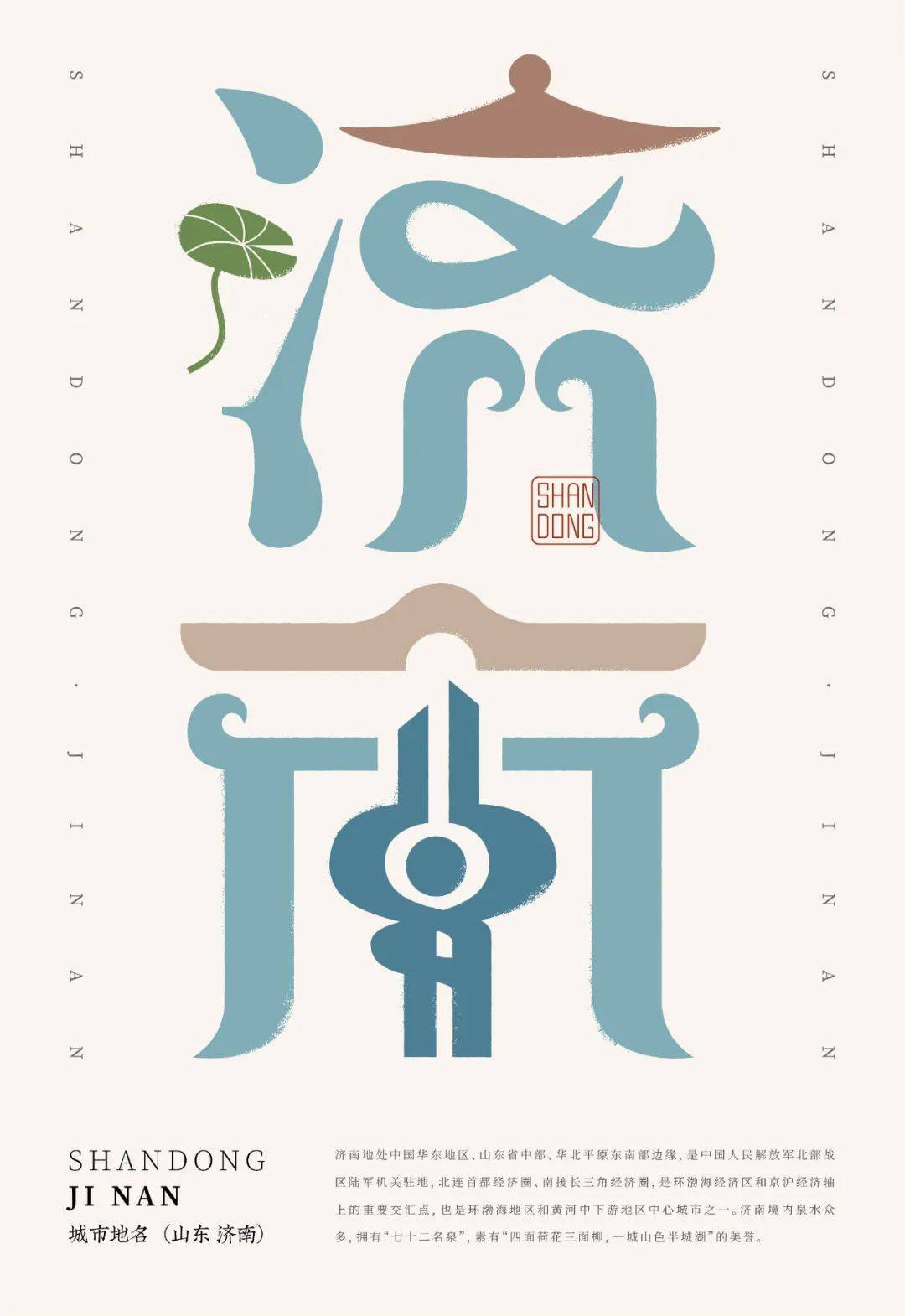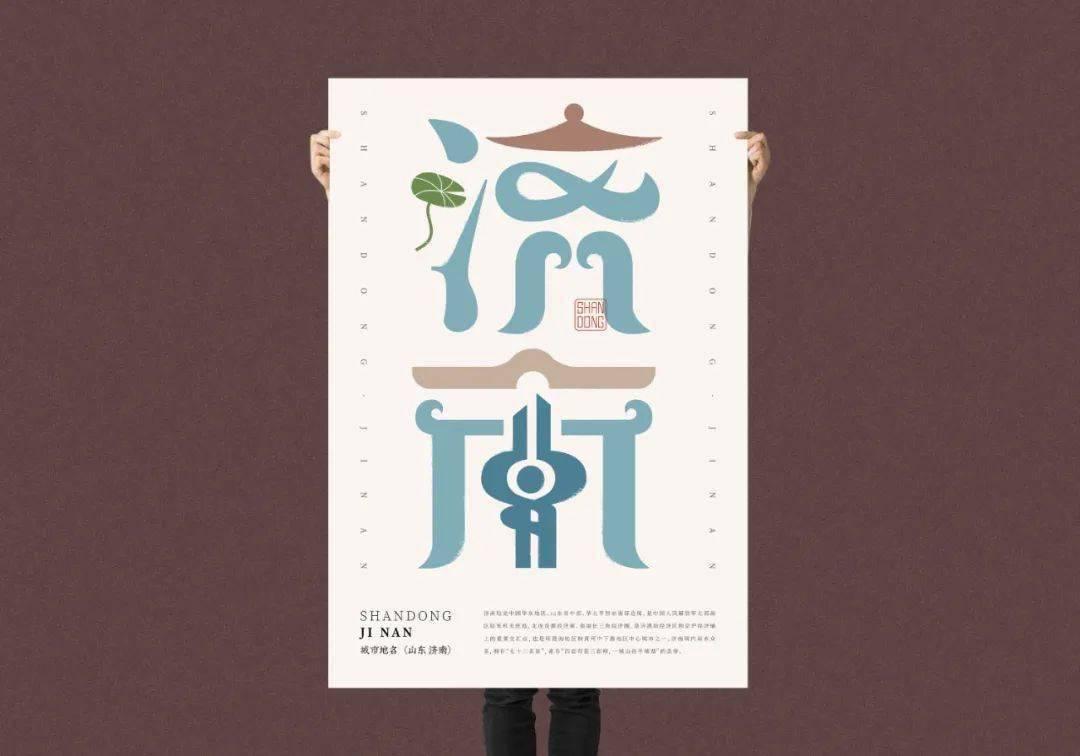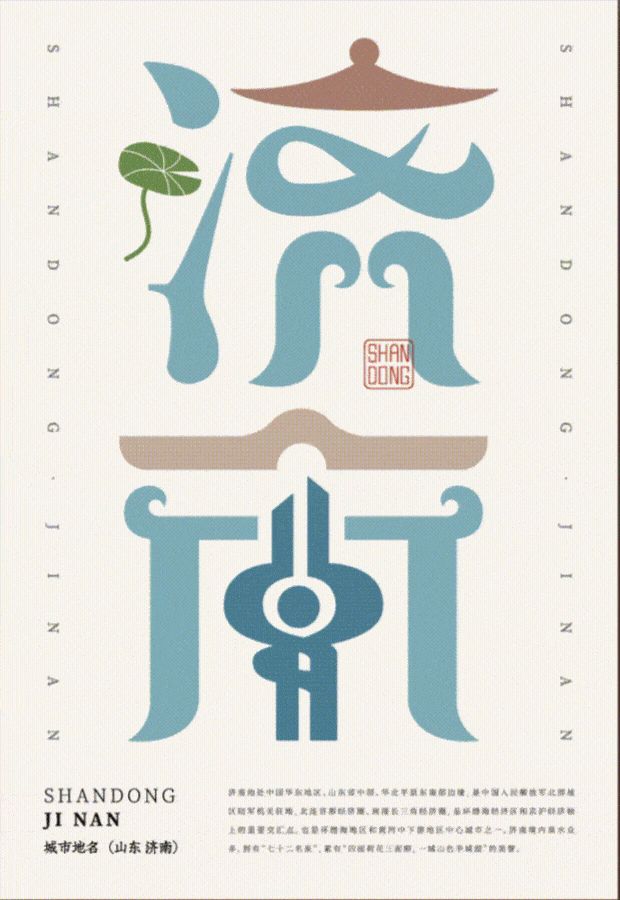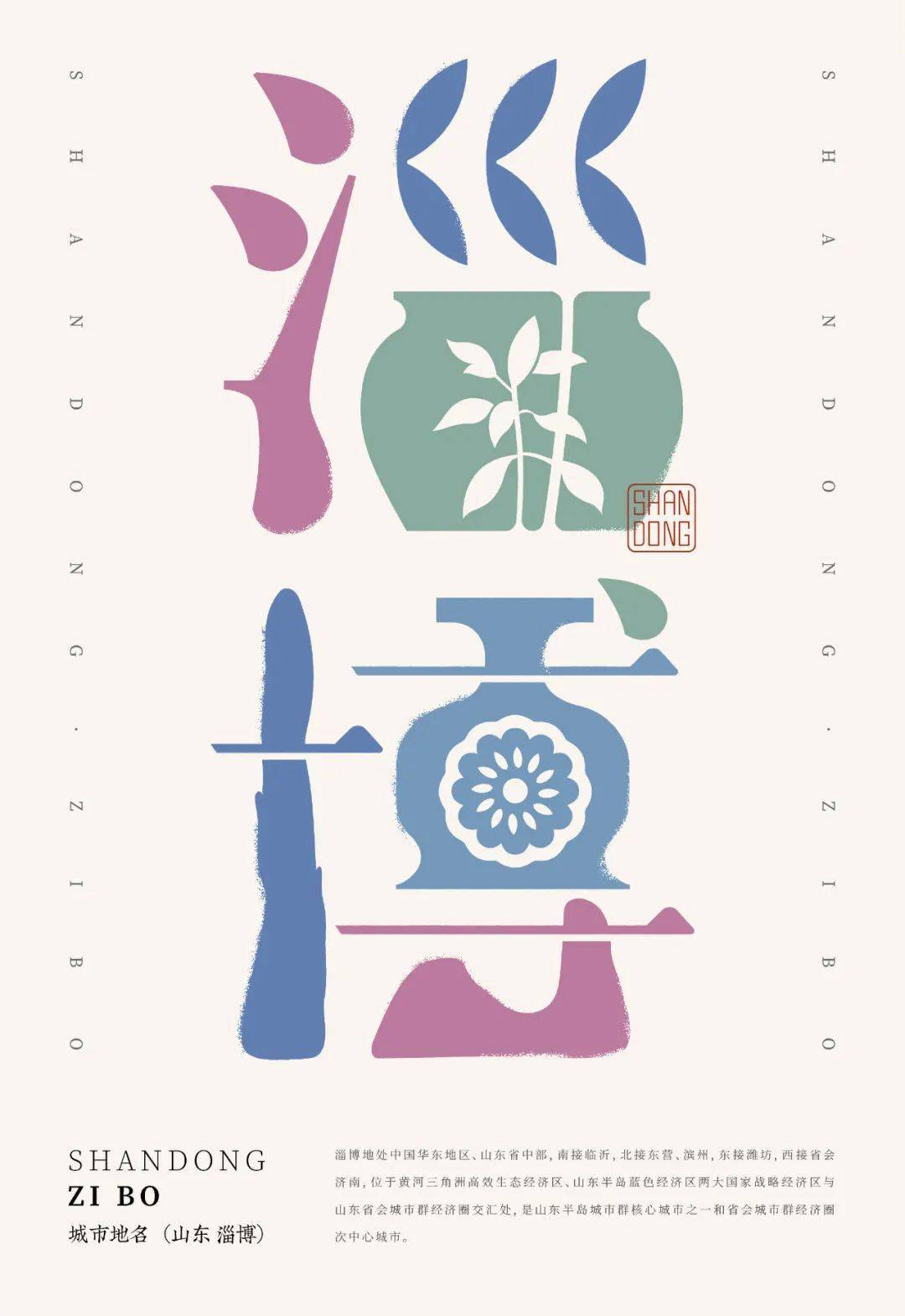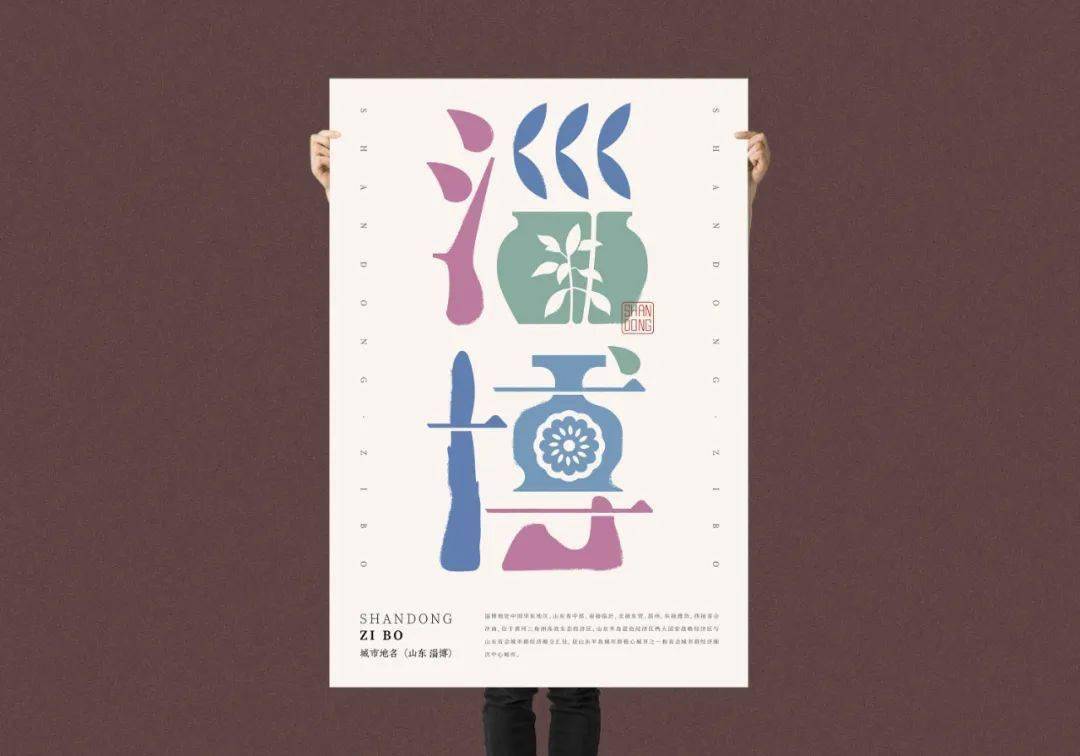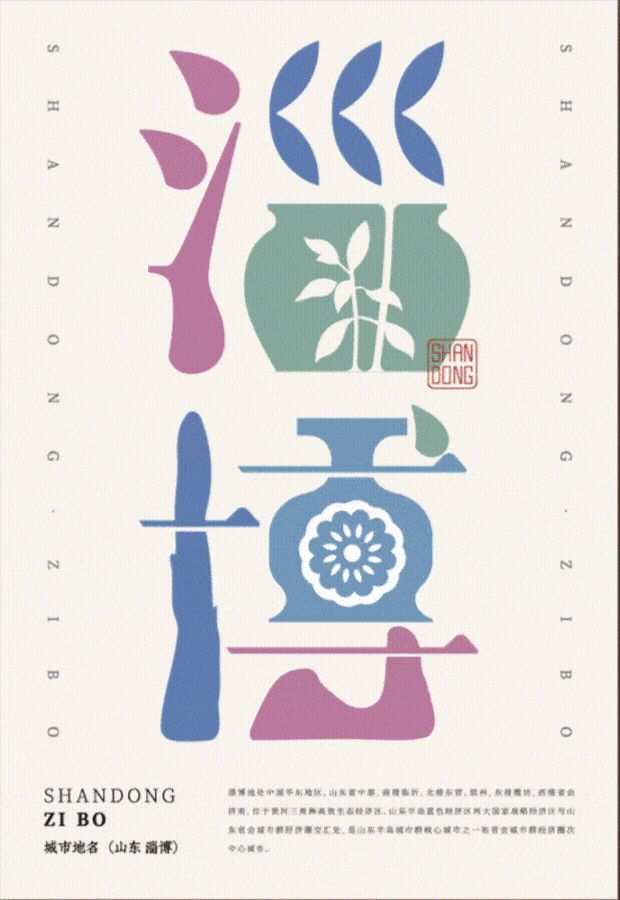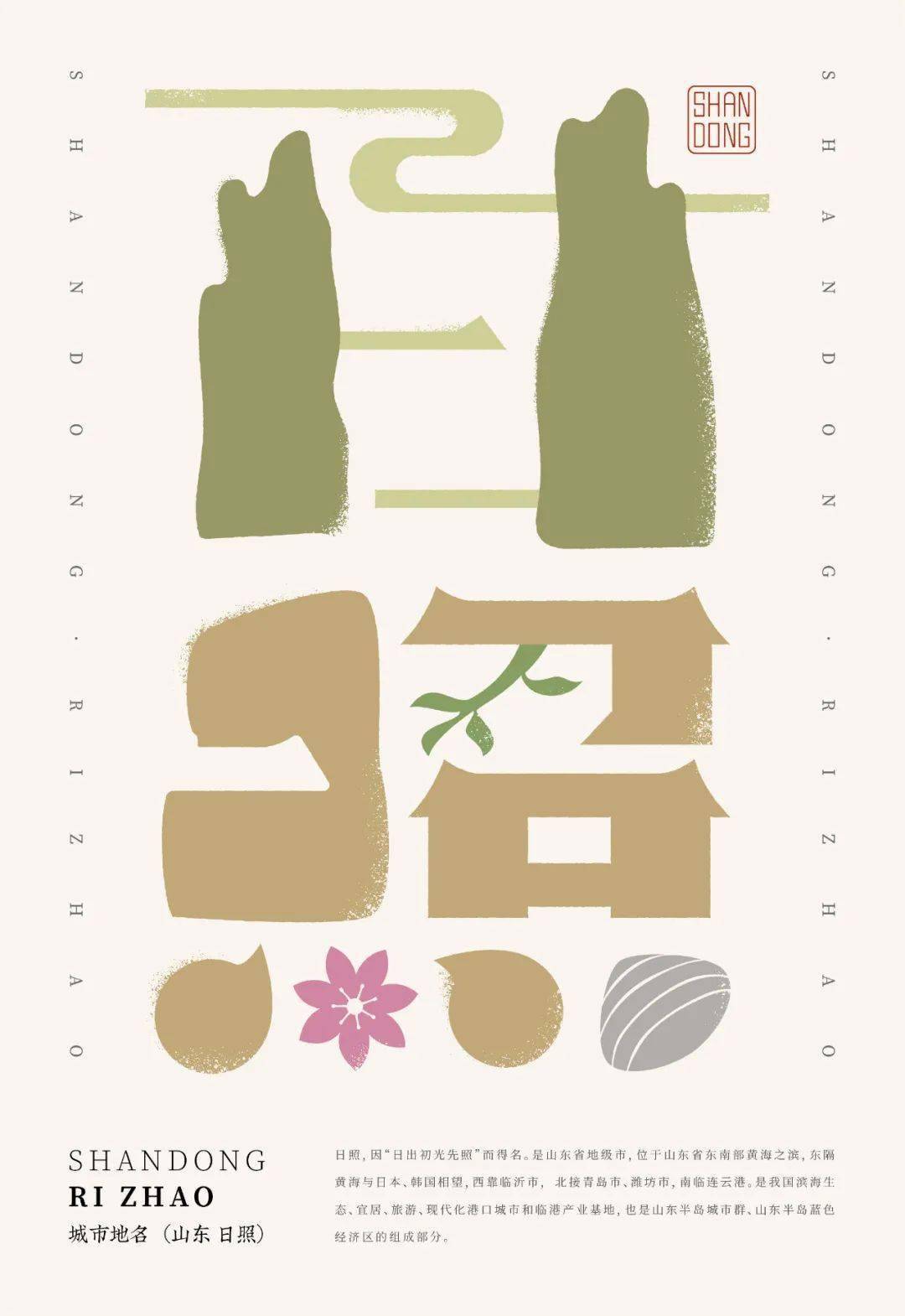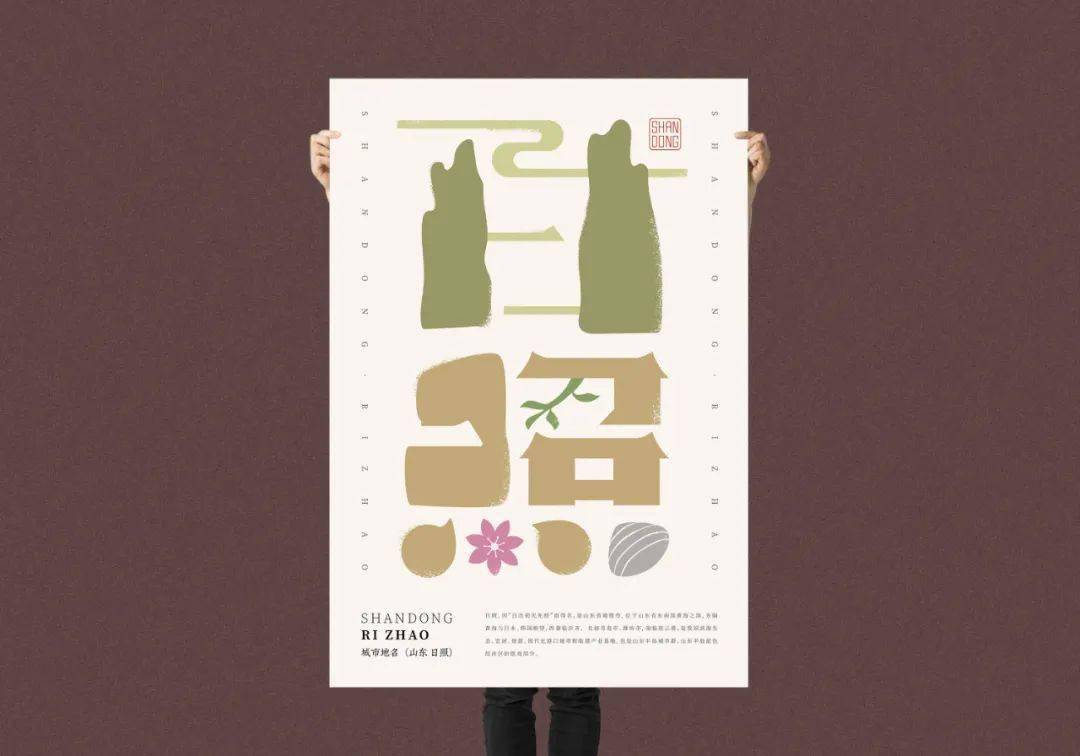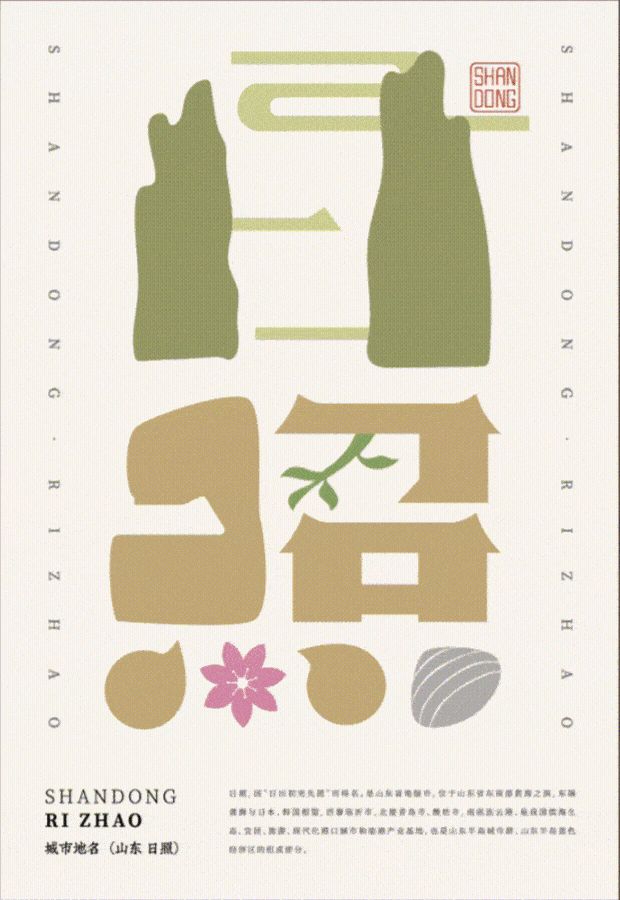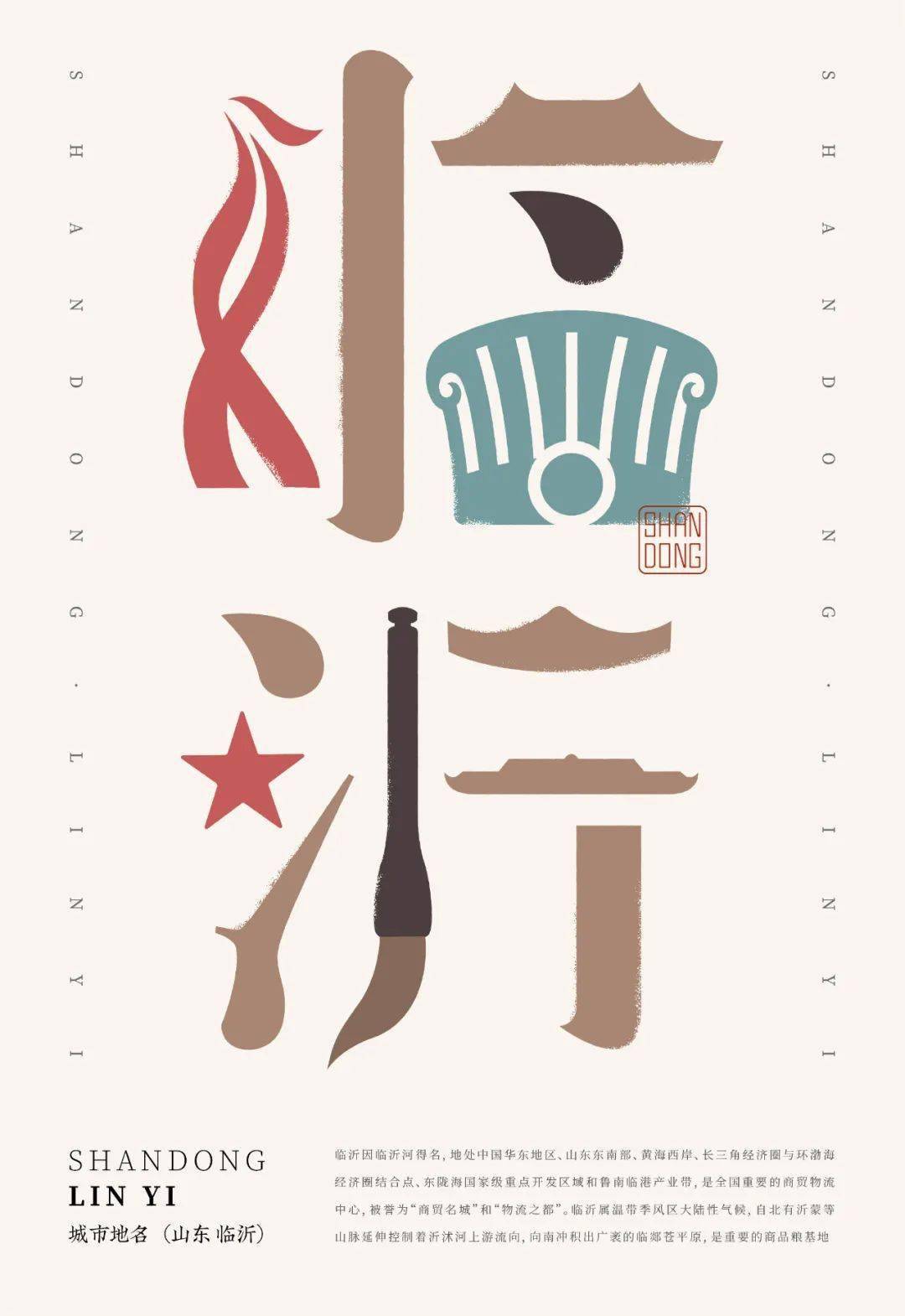
这是工作室近期的一次新尝试,我们将山东省16个地级市做成了字体海报。
当然,每一份字体的设计与创意,都尽可能融合了当地的地域特色和代表性元素。
山东省,简称鲁,位于华东地区,省会济南,位于中国东部沿海北纬34°22.9′-38°24.01′,东经114°47.5′-122°42.3′之间,自北而南与河北、河南、安徽、江苏4省接壤。全省总面积15.79万平方千米,辖16个地级市,分别是:济南、青岛、淄博、枣庄、东营、烟台、潍坊、济宁、泰安、威海、日照、滨州、德州、聊城、临沂、菏泽。
济南市
淄博市
日照市
临沂市
威海市
烟台市
泰安市
菏泽市
东营市
滨州市
德州市
潍坊市
济宁市
青岛市
枣庄市
聊城市
应用效果展示